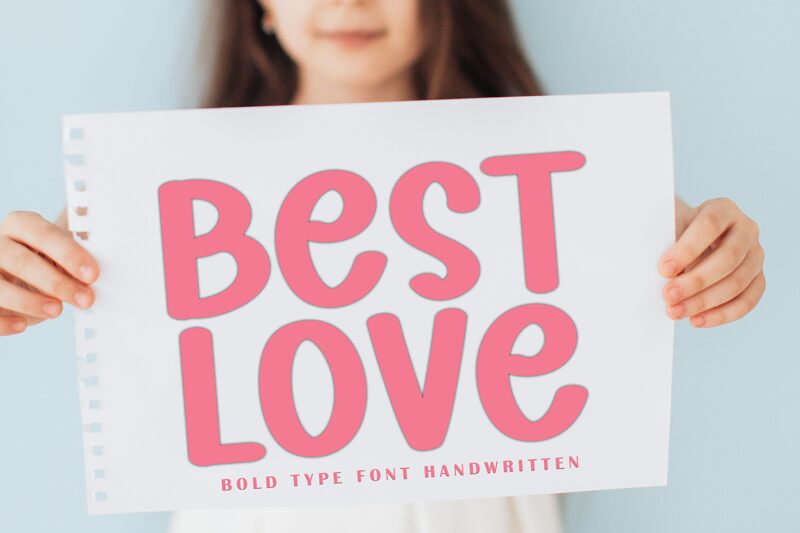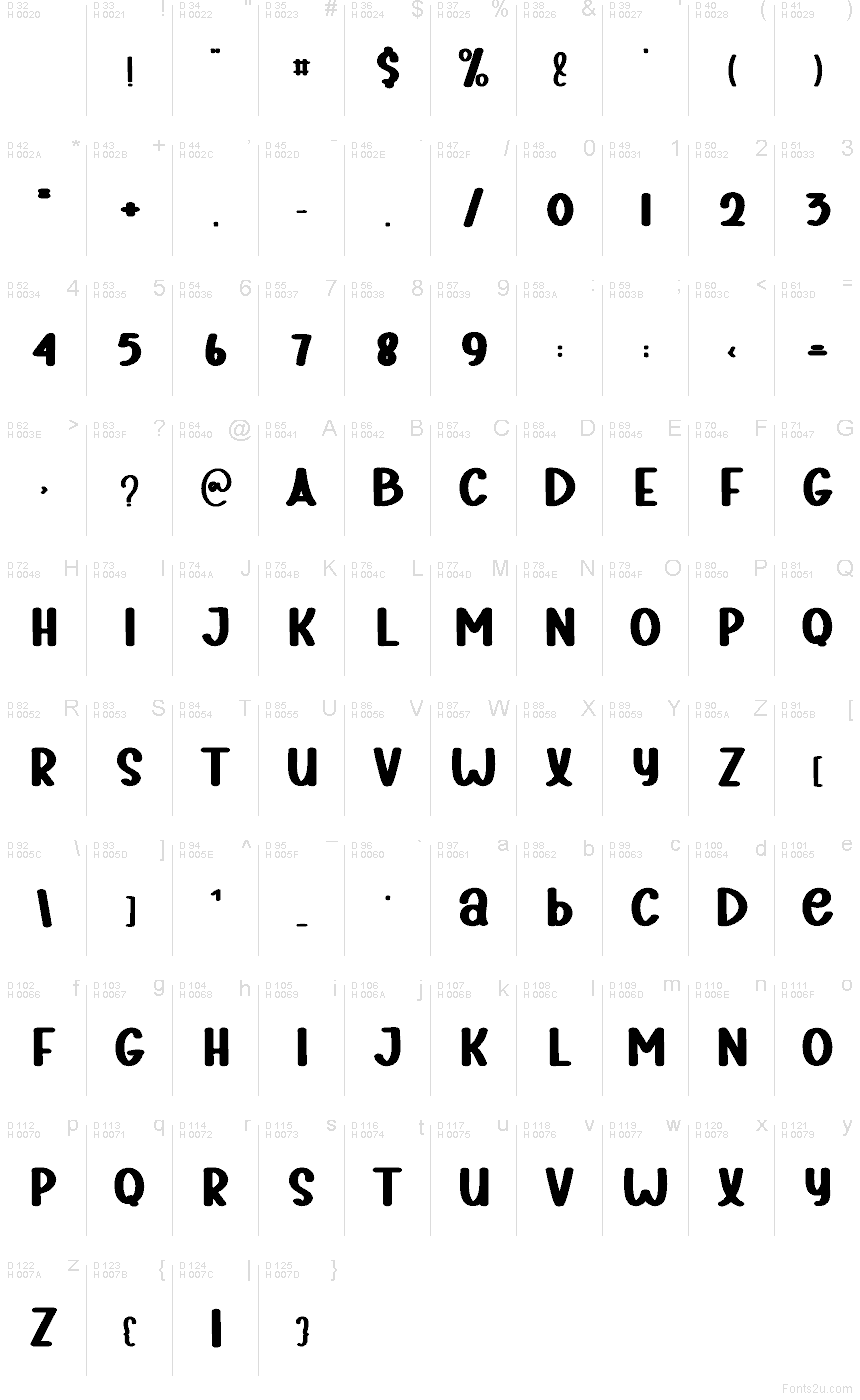
Best Love è un carattere display manoscritto gratuito, caratterizzato da lettere ampie e cariche d'inchiostro, con curve morbide e piene. Gli spessori irregolari e le giunzioni serrate donano al lettering l'aspetto vivace di una silhouette ritagliata nella carta. Gli spazi interni ridotti gli conferiscono una trama densa e allegra.
Un brand di ristorazione informale o un ristorante per famiglie potrebbero valorizzare questa presenza accogliente e corposa su confezioni, menu e insegne. È una soluzione adatta anche a manifesti per eventi dedicati ai bambini e articoli promozionali giocosi: le sagome arrotondate trasformano il nome in un semplice emblema in stile mascotte, perfetto per rappresentare l'identità del prodotto.